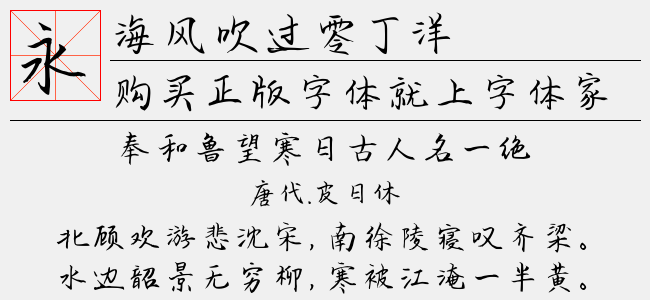
海风吹过零丁洋
字体作者:XFont
字体名称:海风吹过零丁洋
字体家族:X-font系列
书体类型:手写体
海风吹过零丁洋
海风吹过零丁洋是由X-Font出品的一款非常漂亮的艺术字体,工整简洁,具有强烈的视觉冲击力,适应于报纸和杂志和书籍中常用字体, 海报、个性促进品牌标志设计、字体设计、等环境使用,欢迎喜欢的朋友前来字体家下载使用。
海风吹过零丁洋 - 对雨愁闷,寄钱大郎中
海风吹过零丁洋 - 金盘草诗(生宁江巫山南陵林木中)
海风吹过零丁洋 - 奉和圣制幸韦嗣立山庄应制
海风吹过零丁洋 - 大写字母/小写字母/数字